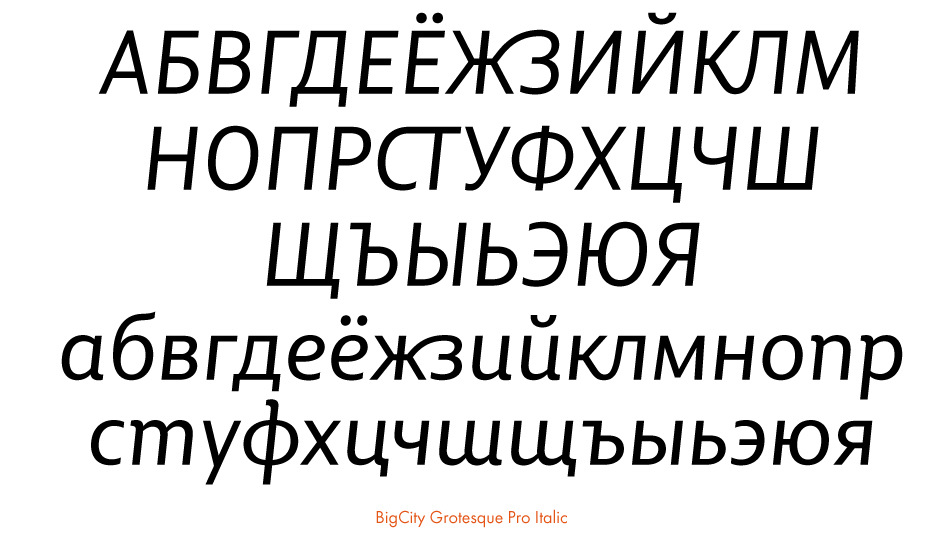
Гротески
Также называются рубленые шрифты, Grotesk (в Германии), Grotesque (в Англии и Франции), Gothic (в Америке). Впервые наборные шрифты без засечек появились в начале XIX века в Англии, хотя подобная форма знаков применялась еще в надписях античной Греции. Вначале применялись исключительно как акцидентные, но в ХХ веке стали использоваться для набора текста. Характеризуются, как правило, малой контрастностью или полным отсутствием визуального контраста между основными и соединительными штрихами. В соответствии с формой овалов, наличием или отсутствием контраста, степенью открытости знаков и степенью разноширинности гротески делятся на старые, новые, геометрические и гуманистические. Иногда к гуманистическим гротескам относят также так называемую ленточную антикву – умеренно контрастный шрифт без засечек, конструкция которого повторяет один из видов антиквы.
Старые гротески
Первый гротеск появился в 1816 году в Англии. Это шрифты с небольшим контрастом, одноширинные, полузакрытые и открытые. Знаки имеют простую и даже грубую геометрическую форму, с крупным очком строчных. Шрифты в целом оставляют впечатление сурового грубого реализма. В некоторых шрифтах только прямые начертания, в других имеются наклонные (не курсивные). Угол наклона знаков средний.
Новые гротески
Новые гротески развивают принципы построения старых гротесков. Они появились в 50-х годах ХХ века и были вызваны к жизни потребностями функциональной швейцарской школы типографики. Новые гротески гораздо изящнее своих предшественников и почти не имеют отличительных черт, что позволяет характеризовать эти шрифты как стандартные и незаметные. Это закрытые одноширинные шрифты почти без контраста, с крупным очком строчных знаков, сильно развитые по начертаниям. Верхние выносные элементы этих шрифтов равны росту прописных знаков. Как правило, в новых гротесках применяются наклонные начертания (не курсивные).
Открытые гротески
Самый новый и самый современный тип гротесков. Общая черта
для всех разновидностей таких гротесков — открытость и негеометричность форм. Кроме того, довольно многие из них обладают
небольшим контрастом; только в открытых гротесках встречаются
скошенные срезы вертикальных штрихов.
Разновидностью открытых гротесков являются
гротески — тип гротесков, наиболее близкий по форме к антикве (а имен-
но к гуманистической/ренессансной антикве). Появились они как реакция на чрезмерно геометризированную форму геометрических гротесков, в 30-х годах ХХ века в Англии появились гротески нового типа, форма, структура и пропорции которых непосредственно базировались на конструкции антиквы старого стиля. В последнее время эти гротески получили широкое распространение как самостоятельные гарнитуры, так и в составе супергарнитур, которые разрабатываются как системно связанные шрифты различных классификационных групп (например, антиква и гротеск). Гуманистические гротески обычно имеют открытый рисунок и некоторый контраст между штрихами. Как правило, они разноширинные с не очень большим очком строчных, но бывают исключения, особенно для компактных шрифтов узких пропорций. Большинство этих шрифтов имеют настоящие курсивные начертания. Углы наклона знаков в курсивах могут быть малые или средние.
Механистические гротески
Антиква-гротески
Акцидентные и текстовые шрифты, по форме промежуточные между гротеском и антиквой. Имеют на концах штрихов либо едва заметные утолщения, либо маленькие острые засечки.
Геометрические
Геометрические гротески принципиально строятся на основе простейших геометрических форм – окружности, квадрата, равностороннего треугольника. Эти шрифты появились в 30-е годы ХХ века в Германии под воздействием идей конструктивизма и школы дизайна Баухауз.
Моноширинные
Специальные шрифты, все знаки которых имеют одну и ту же толщину (ширину). Применяются для набора таблиц, листинга программ и в других случаях, когда требуется полное совпадение колонок и знаков по вертикали набора.
Гротескный шрифт. «Гротеск» — шрифт рубленый. Примеры
Современные
Он был разработан в то время, когда промышленная революция ускорила развитие полиграфического оборудования. Новые способы производства и обработки металлов позволили инженерам разработать очень впечатляющие и сложные машины, способные выполнять высокоскоростную печать. Тиражи газет были высокими, и, несмотря на мировую войну 1 и , из-за которой ресурсы были скудными, в бурные 20-е годы наблюдался высокий спрос на высококачественную печать, особенно на быстрорастущем рынке досуга, где реклама также становилась все более распространенной.Monotype Grotesque был введен, чтобы удовлетворить потребность в шрифте с авангардным внешним видом, чтобы соответствовать дизайнерским концепциям того времени.